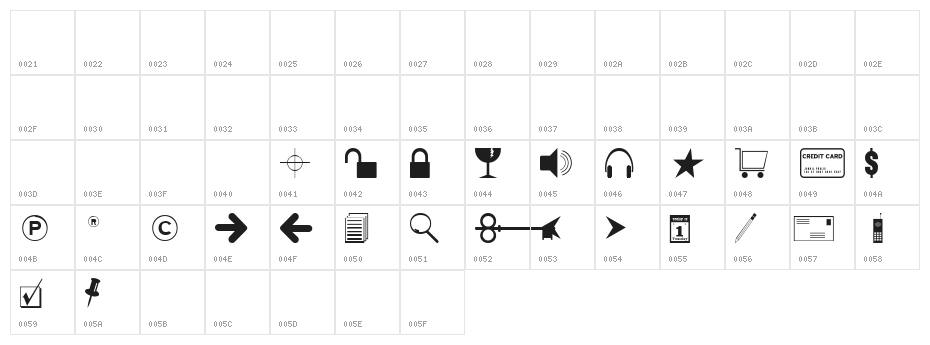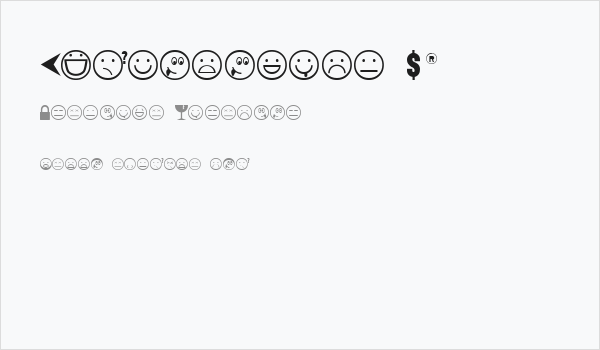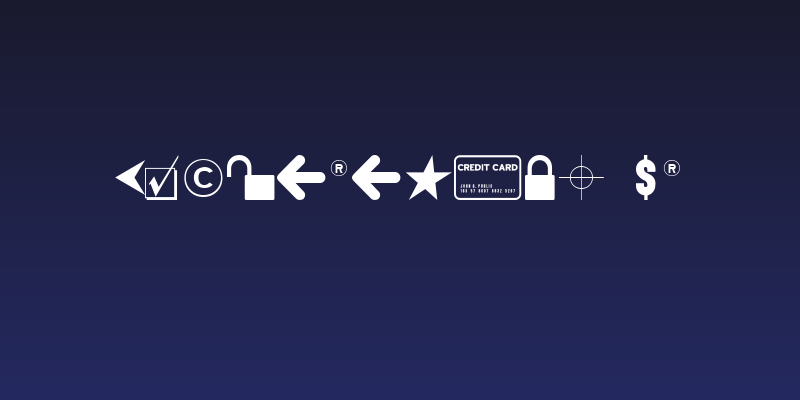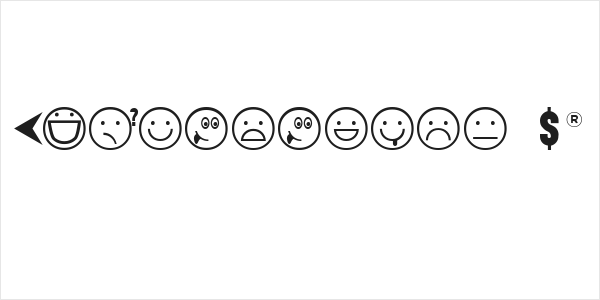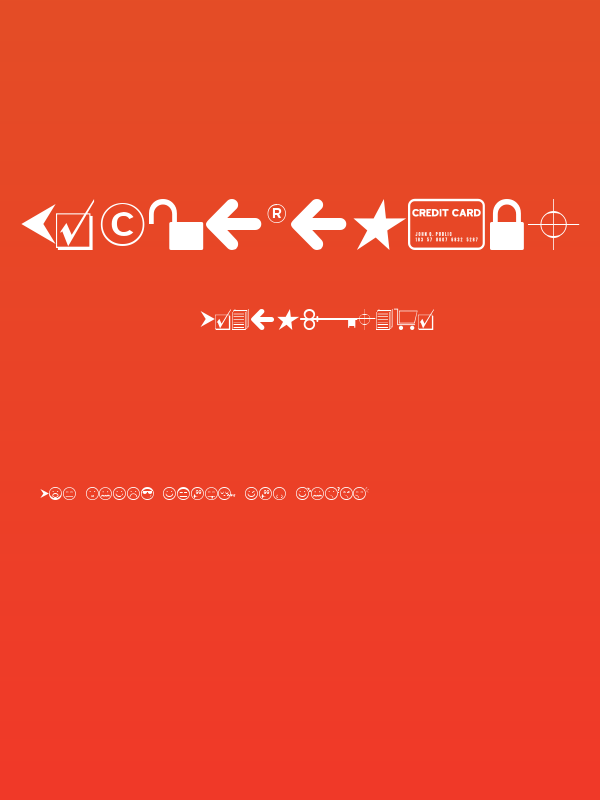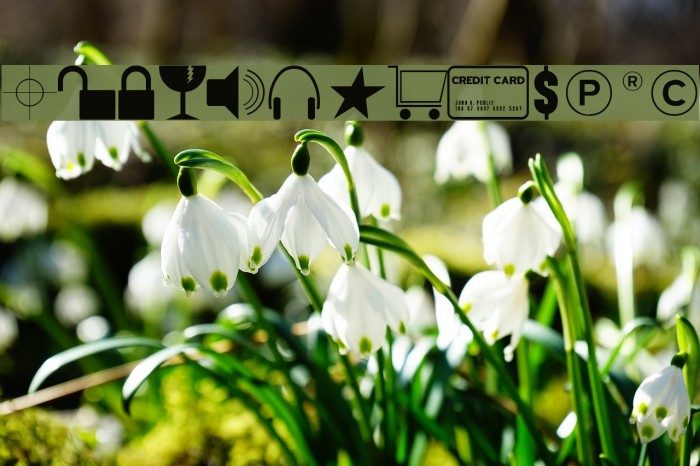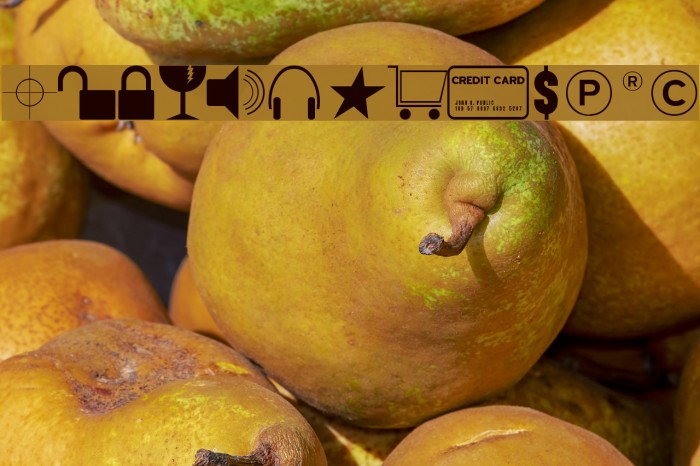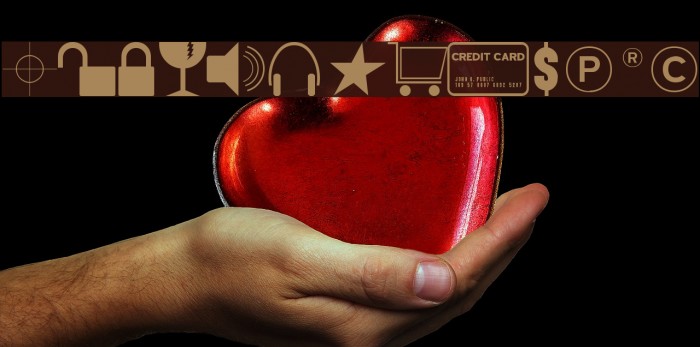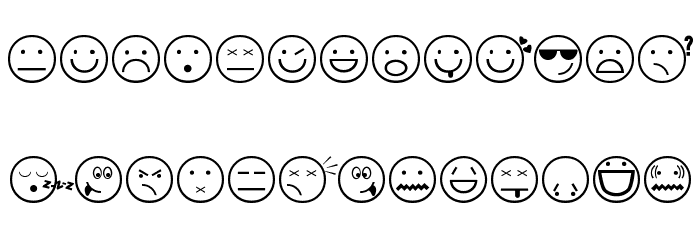
Symbologica JL Font
| Caso d'uso | Icons, Emoticons, Digital Interfaces |
| Progetti proposti | Ideal for use in digital interfaces, educational materials, and communication apps where clear iconography is essential. |